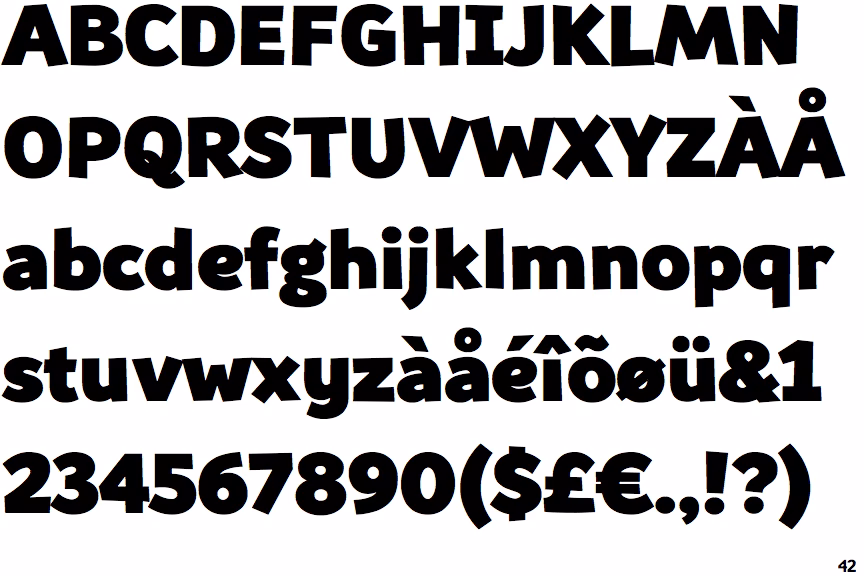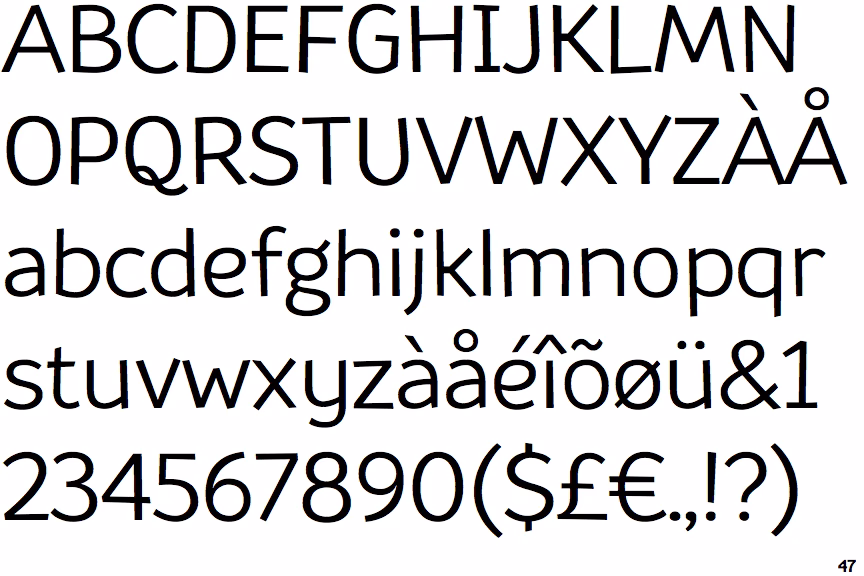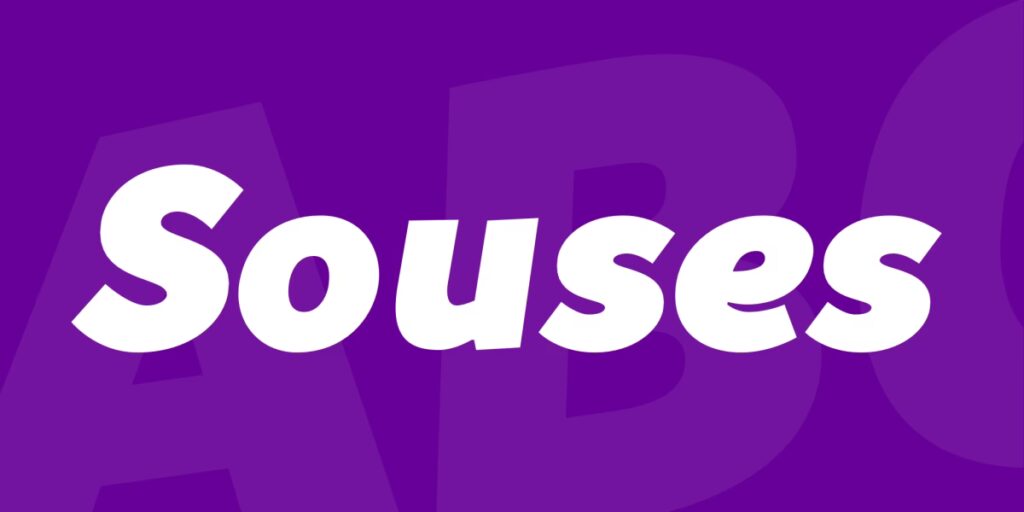
En el vasto universo del diseño gráfico y la creación de contenido, la elección de la tipografía correcta es un pilar fundamental que puede definir el éxito o el fracaso de un proyecto. Una fuente no es solo un conjunto de letras; es la voz visual de un mensaje, capaz de evocar emociones, establecer un tono y captar la atención del espectador. Hoy nos sumergimos en el análisis de una de esas gemas que a menudo encontramos en la red: la fuente Souses. Se trata de una tipografía gratuita, audaz y con una personalidad arrolladora, diseñada para no pasar desapercibida. A lo largo de este artículo, desglosaremos todo lo que necesitas saber sobre Souses, desde sus características estéticas y su conjunto de caracteres hasta los detalles cruciales de su licencia y los mejores proyectos donde puedes implementarla para lograr un impacto máximo.
¿Qué es Exactamente la Tipografía Souses?
Souses no es una fuente común. Es una versión gratuita y específicamente recortada de la familia tipográfica mucho más grande conocida como "TT Souses". Fue creada por el diseñador Jovanny Lemonad y distribuida a través de su fundición tipográfica, typetype.ru. El concepto detrás de Souses es ofrecer a los diseñadores una muestra potente y funcional del carácter de la familia completa, permitiéndoles acceder a una herramienta de alta calidad sin coste alguno. Su diseño se enmarca dentro de la categoría Sans-Serif, caracterizada por la ausencia de remates o serifas en los extremos de los caracteres, lo que le confiere un aspecto limpio y contemporáneo.
Lo que realmente distingue a Souses es su estilo audaz e inclinado. No es una cursiva tradicional, sino que toda su estructura está diseñada con una inclinación dinámica que transmite una sensación de movimiento, energía y urgencia. Es una fuente que grita modernidad y confianza, ideal para marcas y proyectos que buscan proyectar una imagen fuerte y decidida.
Características Visuales y Estilo Único
Para entender el poder de Souses, es esencial analizar sus atributos visuales. Cada elemento ha sido cuidadosamente diseñado para contribuir a su presencia imponente.
Modernidad y Dinamismo
La combinación de un grosor audaz (Bold) y una inclinación constante es la fórmula de Souses para el dinamismo. Esta inclinación no se siente como un efecto añadido, sino como parte integral del ADN de cada letra. Esto la hace perfecta para industrias relacionadas con la tecnología, los deportes, los videojuegos o cualquier campo que valore la velocidad y la innovación. Su apariencia es asertiva y directa, eliminando cualquier ambigüedad en su comunicación.
Impacto y Legibilidad
Souses está concebida como una fuente de exhibición (display font). Esto significa que su principal fortaleza reside en su uso a gran tamaño, como en titulares, logotipos y carteles. En estos contextos, su legibilidad es excelente y su impacto visual es innegable. Sin embargo, debido a su grosor y estilo distintivo, no es la opción más recomendable para bloques de texto largos o párrafos (body text), ya que podría resultar visualmente agotador y dificultar la lectura prolongada.
Consistencia Visual
Un aspecto clave de su diseño es la consistencia en el peso de los trazos. Tanto las letras mayúsculas como las minúsculas, así como los números y símbolos, mantienen un grosor uniforme. Esta coherencia asegura que ningún carácter desentone, creando un bloque visual sólido y armonioso, fundamental para proyectos de branding donde la consistencia es reina.
Un Vistazo Detallado: Glifos y Conjunto de Caracteres
Una tipografía es tan útil como completo sea su conjunto de caracteres. En este aspecto, Souses no decepciona. La versión 1.000 de la fuente gratuita incluye un total de 416 glifos. Este número es bastante generoso para una fuente gratuita y le otorga una gran versatilidad.
El conjunto de caracteres abarca mucho más que el alfabeto básico. Incluye:
- Letras mayúsculas y minúsculas del alfabeto latino.
- Un amplio soporte para caracteres latinos extendidos (con diacríticos como Ā, ă, Ą, ć, Č, ď, Đ, ē, etc.), lo que garantiza su uso en múltiples idiomas europeos.
- El alfabeto cirílico completo, tanto en mayúsculas como en minúsculas (А, Б, В, Г, Д...), haciéndola viable para proyectos destinados a Europa del Este.
- Números, signos de puntuación y una variedad de símbolos especiales, todos diseñados manteniendo el estilo audaz y coherente de la fuente.
Esta amplia cobertura lingüística es un diferenciador importante, permitiendo a los diseñadores mantener una identidad visual consistente en proyectos internacionales.